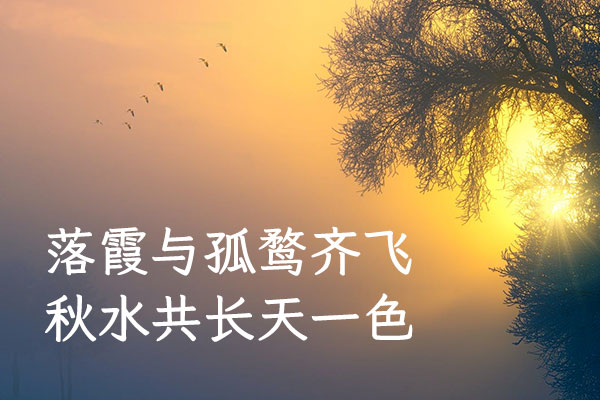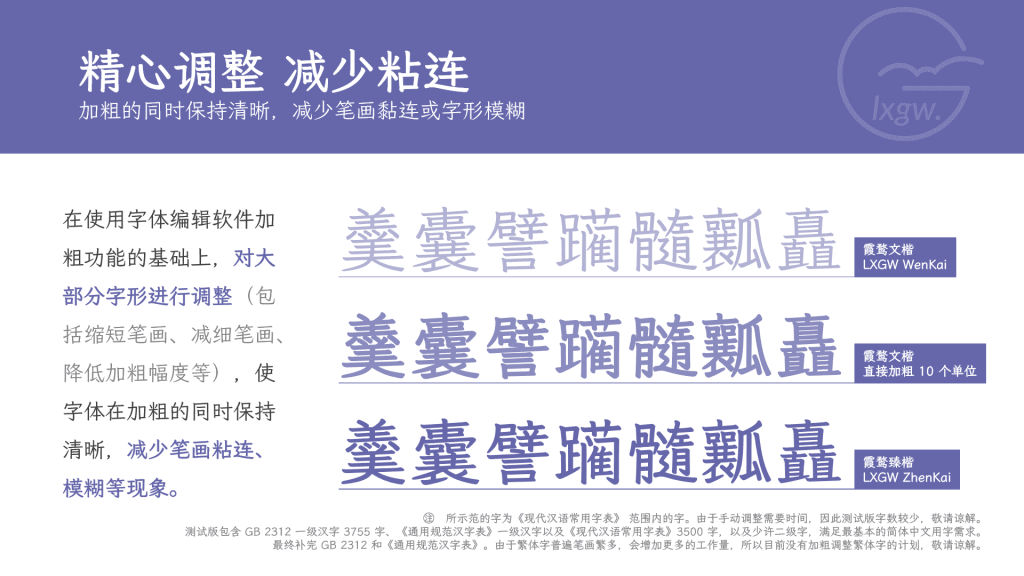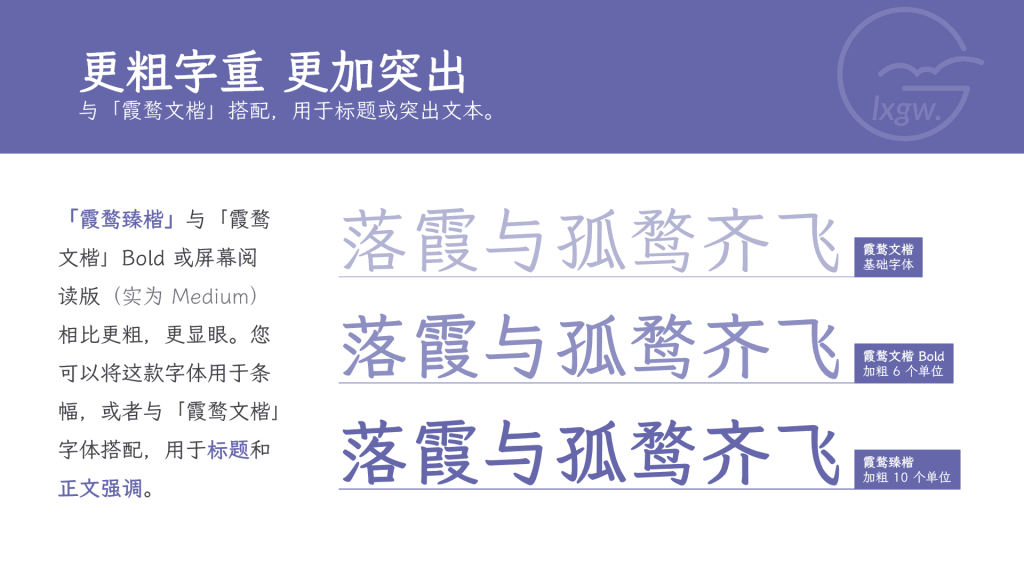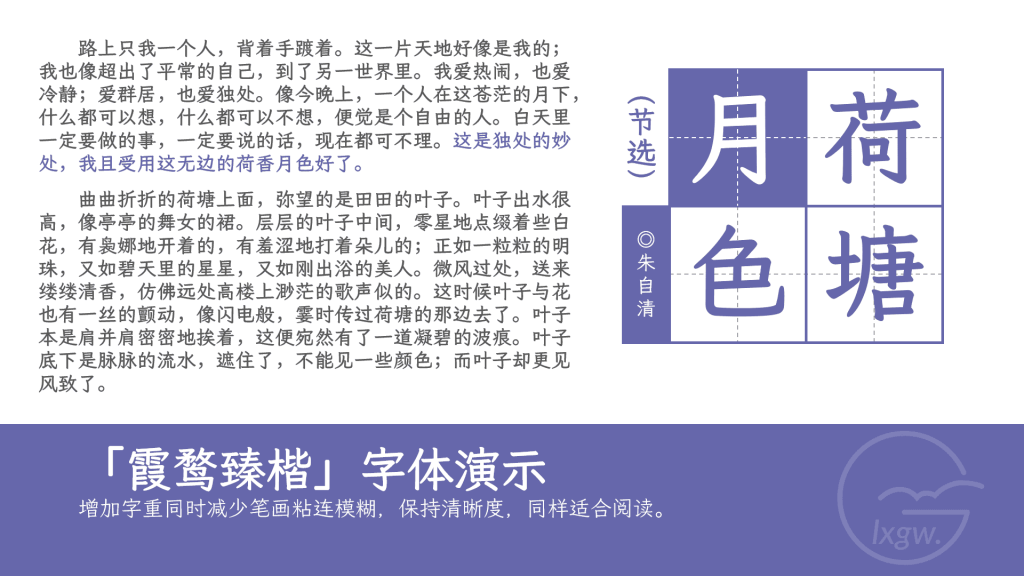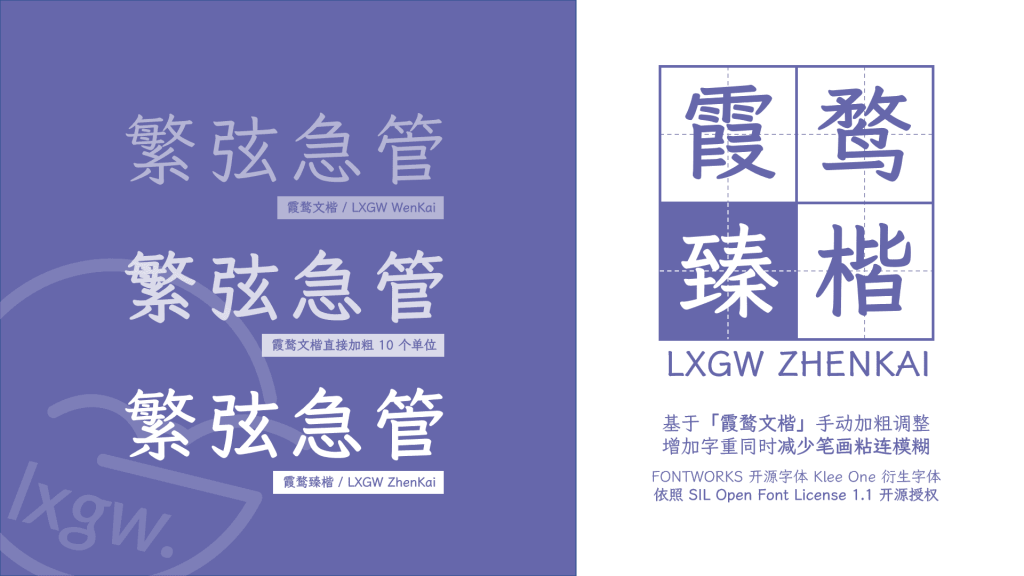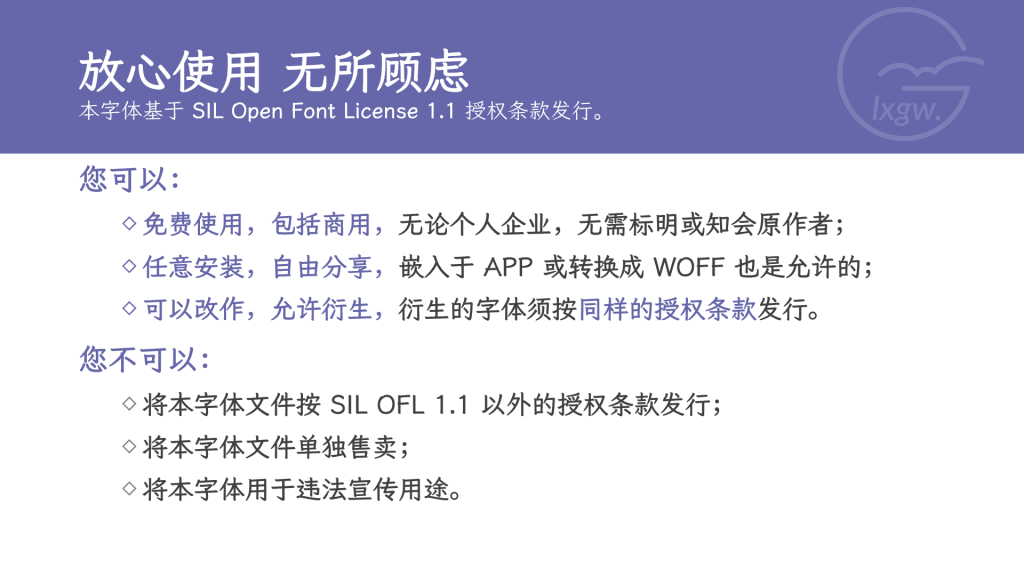
霞鹜臻楷
孤鹜先森是一位才华横溢的字体设计师,他近期推出了一个新的字体——霞鹜臻楷。这款字体的诞生源于一个需求,许多用户反映霞鹜文楷的Bold字重在某些软件中显示过于纤细,难以满足他们的使用需求。为了解决这个问题,孤鹜先森决定尝试制作一款粗字重的字体,于是就有了霞鹜臻楷。
霞鹜臻楷是在霞鹜文楷的基础上进行粗字重制作的尝试。它不仅加粗了字体,还对大部分字形进行了调整,如缩短笔画、减细笔画、降低加粗幅度等,以确保字体在加粗的同时保持清晰,减少笔画黏连、模糊、毛刺等问题。这种精心打磨的字体,让人一看就感受到了设计师的用心和诚意。
霞鹜臻楷效果预览
霞鹜臻楷字体效果预览